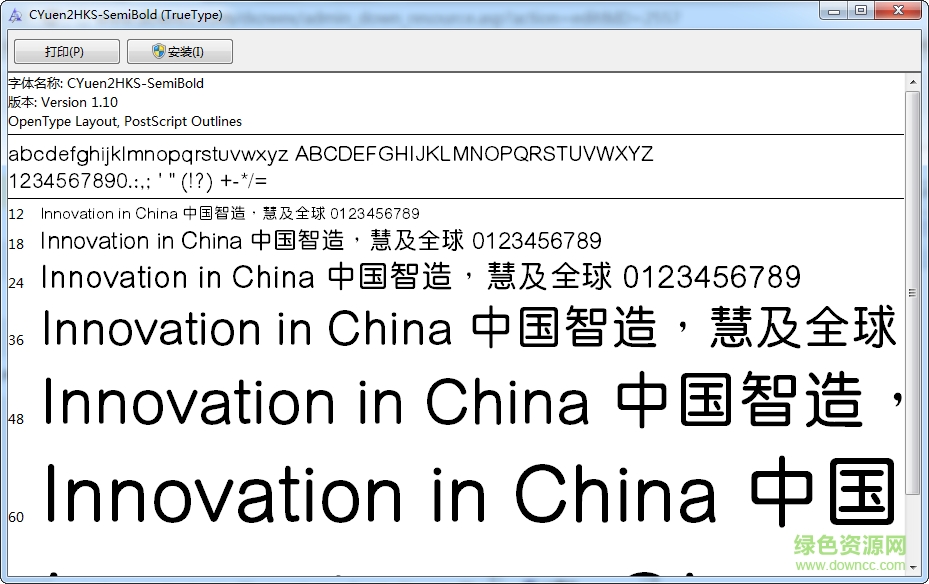
蒙納簡圓黑二體是一款為設(shè)計師們打造的字體軟件,適用于書、報刊的大標(biāo)題,方正美黑簡體字體修長端正,莊重大方。歡迎喜歡的朋友在綠色資源網(wǎng)下載使用!
該字形簡潔的蒙納字體,字體樣式美觀大方,字體結(jié)構(gòu)簡單,字體線條偏細(xì),整體效果很好!適用于平面廣告、產(chǎn)品包裝、書籍印刷等行業(yè)!